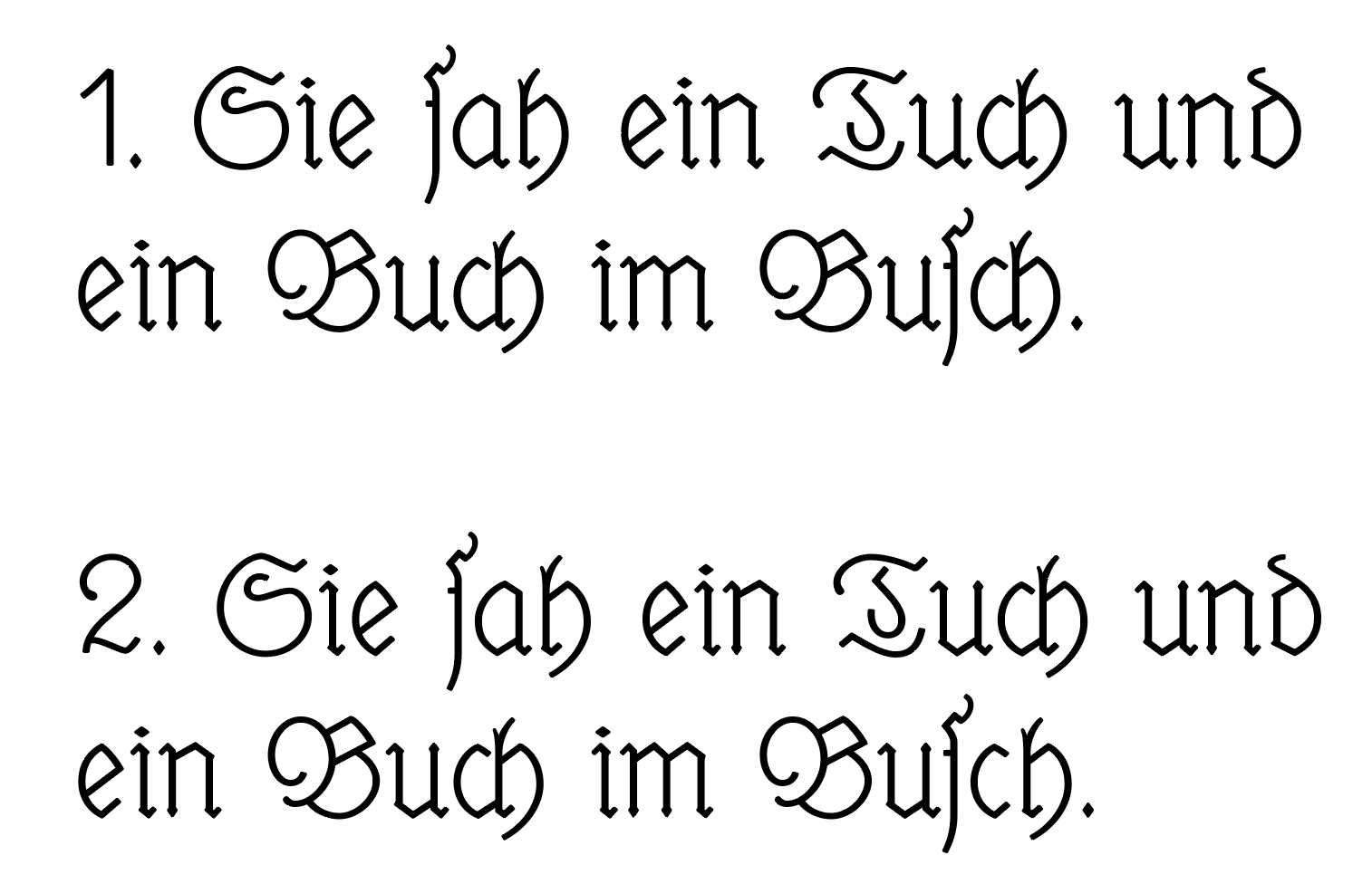
Schriftdehnung im glatten Satz
@ catfonts: Gerade diese Mischung geschieht ja nun in der neuen Version meines Programms. Im verlinkten Video fehlte die Möglichkeit, Schrift horizontal zu skalieren, weshalb dort die Abstände zum Teil auch noch über die eigentlich gesetzten Grenzen hinausgehen. Nun erfolgt zunächst eine Verminderung oder Erweiterung der Wortzwischenräume bis zu den gesetzten Grenzen (0,8 bis 1,6 von 1/4 Geviert). Insofern dies nicht ausreicht, wird die gesamte Zeile (also sowohl Schrift als auch die Wortzwischenräume) um bis zu 2% gedehnt oder gestaucht. Und die Ausgangsfrage dieses Threads war ja. ob das überhaupt als zulässig betrachtet wird.
Es stellt sich die Frage, ob die Grenzen noch enger zu fassen sind (ursprünglich waren sie 0,8 bis 1,8; siehe erste Probe weiter oben). Dann habe ich sie auf (0,8 bis 1,6 reduziert). Fasse ich die Grenzen allerdings noch enger, reichen die 2% möglicherweise zum Ausgleich nicht mehr aus. Denn ich bin leider auf relativ kurze Zeilen beschränkt. Schon die nun gewählte Zeilenlänge ergibt ein eher zu kleines Schriftbild, was der Leserlichkeit auch nicht gerade förderlich ist.
Ich fürchte, ich werde mit Kompromissen leben müssen.
Insgesamt ist das, was ich mache, ziemlich experimentell. Und ich mag es, Texte, Schriften und Effekte zu kombinieren, um zu sehen, wie sie in Kontrast zueinander treten oder auch harmonieren. Nicht jedes Experiment gelingt. Und ich kann es schon gar nicht allen Recht machen. Ist halt so. 🙂
Das finde ich auch prima, ohne Experimente findet keine Entwicklung statt.
Um nicht zu verallgemeinern: Für mich stellt es sich so dar, dass du an winzig kleinen Stellen schraubst, die ich als Betrachter aber gar nicht mitbekommen kann, weil ich von der Animation so abgelenkt bin, dass ich weder den Text lesen noch Abstände bemerken kann. Drum ist es für mich auch wenig sinnstiftend, mich über einen statischen Screenshot zu unterhalten, den ich so aber nie zu Gesicht bekomme.
Im Grunde ist dies ja die Methode, die bei handschriftlich erstellten Büchern gemacht wurde Auch hier wurden die Glyphen durch gestreckte oder gestauchte Versionen ersetzt, Buchstabenabstände variiert und mit Ligaturen und Abbrevaturen eingesetzt wurden, oder eben, um eine Zeile zu füllen auch nicht.
Gutenberg hatte dies ja soweit möglich nachempfunden, und so ein meisterhaftes Ergebnis, wenn auch mit recht unpraktischem Setzkasten erzielt. Aber die Weiterentwicklung und Normierung der Bleilettern zwangen eben zu einem starren Rahmen, bei dem dann nur Spartien und ein geschickter Ligatur-Einsatz möglich waren.
Heute, mit digitalen Schriften haben wir eben die Möglichkeiten, mit minimalem Stauchen und Strecken zu arbeiten, vielleicht wird es ja auch möglich, dass variable Schriftarten das auch durch eine Interpolation der Glyphen selber zu machen, damit sich die Senkrechten der Buchstaben dann nicht sichtbar in ihren Proportionen ändert. Also die normale Schrift sich nur minimal in Richtung wide oder condensed verändert wird, statt die ganze Glyphe einfach zu strecken oder zu stauchen.
Naja, nicht unbedingt ersetzt. Das ist ja eher ein dynamischer Prozess. Außerdem habe ich ja handschriftlich durch die Feder eine einheitliche Strichbreite und mit ein paar Tricks kann ich auch den Grauwert bei großen oder breiten Buchstaben beeinflussen. Und das geht digital bekanntlich nicht, weswegen man eben nur sehr begrenzten Spielraum (1–3%) hat.
Ich kann nichts zum Satz sagen, so etwas prüfe ich lieber auf Papier. Von der st-Ligatur aber möchte ich aus Erfahrung als Leser abraten. Lesen geht am besten in gewohnten Textformen. Diese st-Ligatur ist eine reine Schmuckligatur, die für Überschriften oder sehr, sehr kurze Texte, kürzer als ein Gedicht, und für große Schriftgrade gedacht ist. In Brotschriftgraden hat es früher, im Bleisatz, so etwas aus gutem Grund nicht gegeben. Erst ab Steckschriftgröße, also 16, vielleicht auch mal 14 Punkt. Sobald drei solche »st« auf engem Raum auftreten, wird der Schmuck lästig. Ich würde solch einen Text nicht lesen können, weil ich in einem fort daran erinnert werde, daß jemand absichtsvoll in den gewohnten Leseprozeß eingreift, also als würde der Setzer unentwegt »Hallo, hier bin ich!« rufen. »Und ich habe eine Ligatur im Setzkasten gefunden, die du noch nicht kennst. Schau hier, noch mal. Und hier wieder! Achtung, jetzt! ...«
Ich erinnere an das Bonmot von Frutiger, das für längere Texte wie für ein einzelnes Zeichen gelten kann: »Schrift ist wie ein Löffel: wenn ich mich am Abend an die Form des Löffels erinnere, mit dem ich am Mittag meine Suppe gegessen habe, dann war es eine schlechte Löffelform.«
Zur ch-Ligatur möchte ich als Bleisetzer, der die Ligatur aus dem Kasten greift, also absichtsvoll einsetzt, bemerken, daß sie nicht für »sch« verwendet werden sollte, weil die Trennung von »s« und »ch« die Lautbildung zumindest theoretisch irritiert. Man liest sicherlich darüber hinweg, aber es widerspricht der Absicht. In Fraktur gab es im Bleisatz eine sch-Ligatur, in Antiqua nicht oder sehr selten. Es ist besser, eine sichtbare ch-Ligatur nicht zu verwenden, wenn sie automatisch eingesetzt wird.
Wäre aber sicherlich digital leichter umzusetzen, als mit Bleilettern, ließe sich so eine Weitenanpassung, ohne dass dabei überbreite oder deutlich zu enge Buchstabenabstände, oder eine Veränderung der Strichstärke der Glyphen entsteht ja über variable Fonts lösen. siehe https://v-fonts.com/